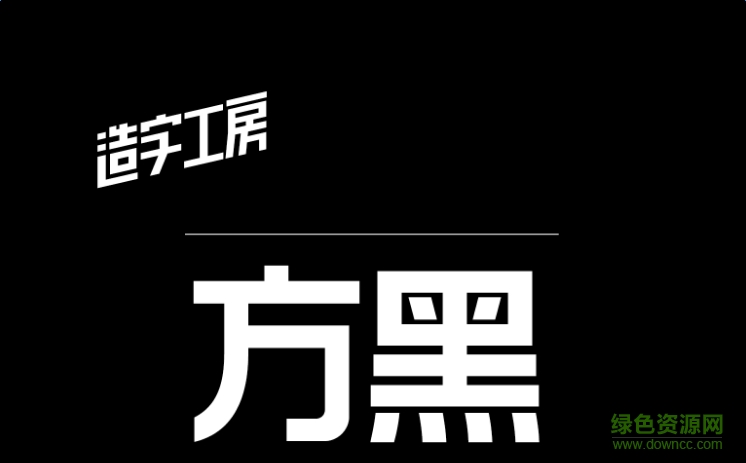
造字工房方黑体是一款造字工房类稳重优雅风格字体软件,尚雅宋体整体效果沉稳有劲,非常醒目,在广告大标题设计方面有着不错的应用,同时也深受广大书法家的喜爱,还有更多好看字体尽情期待,欢迎到绿色资源网下载体验!
造字工房方黑体在常见的黑体字形风格之上更加平稳着力,个性鲜明,笔画简洁、大方,引人注目。字形结构严谨,实用性强,横竖笔画基本保持一致,凸显出精简精干的特点。适用于标题、广告或副标题用字。